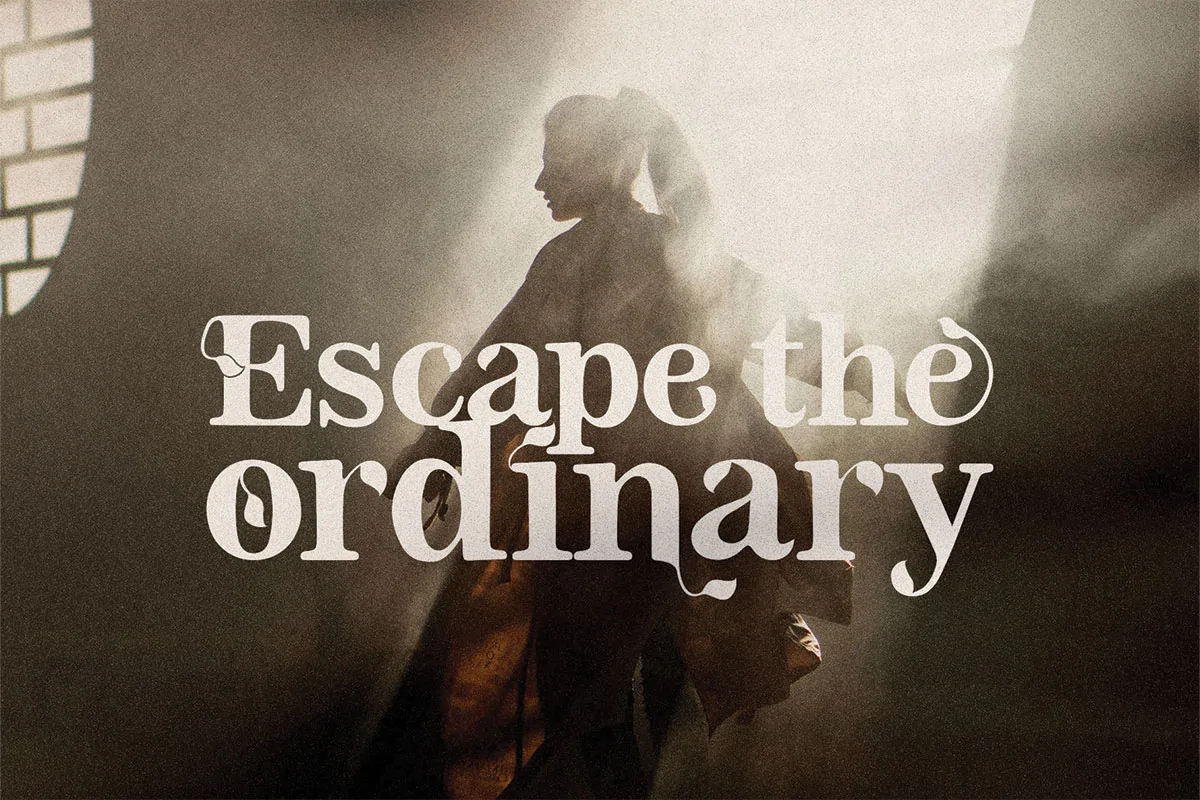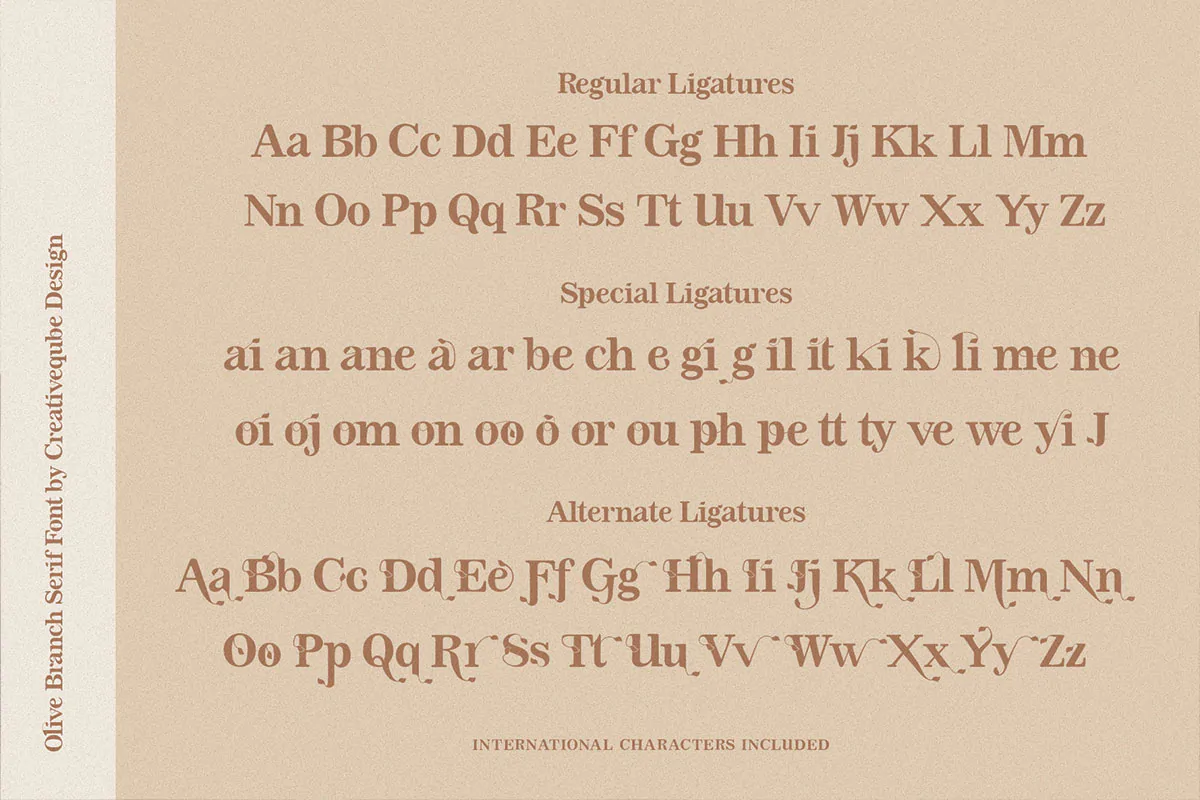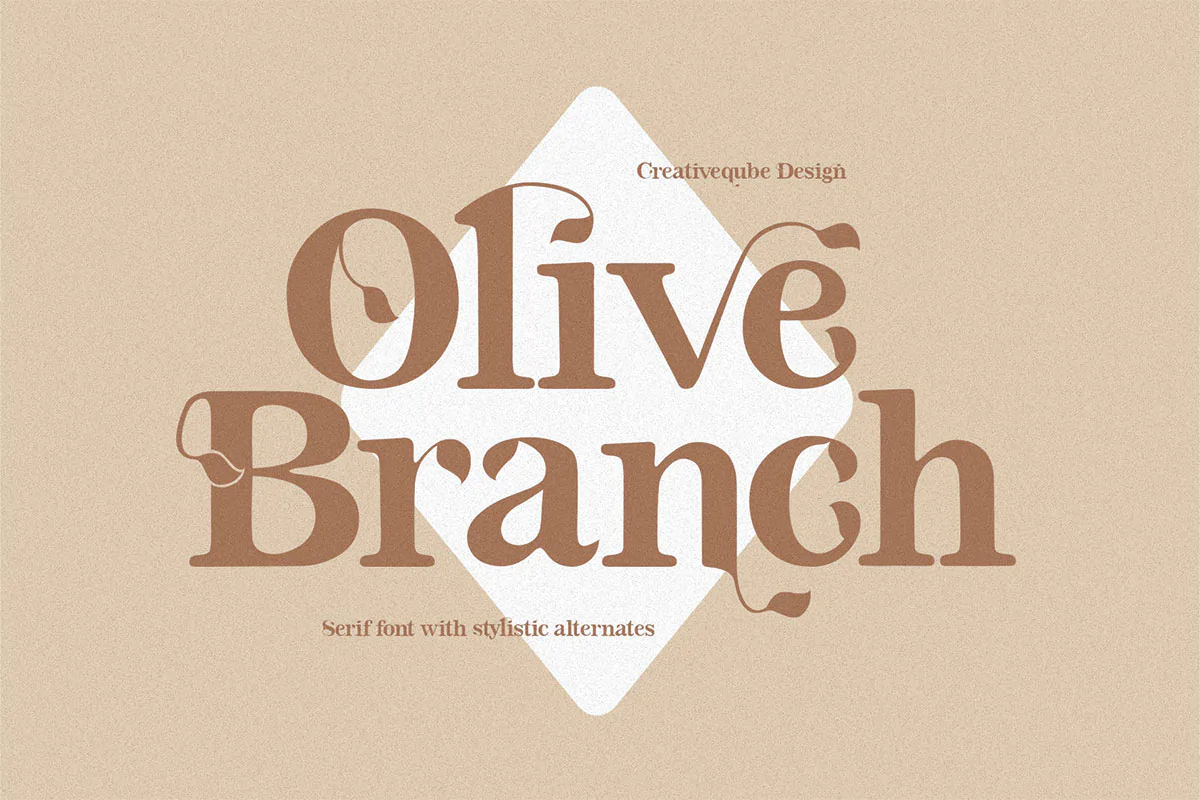
فونت تزئینی شاخه زیتون Olive Branch
فونت تزئینی شاخه زیتون
فونت تزئینی شاخه زیتون Olive Branch یک سریف فونت انگلیسی فوق العاده زیبا است که به سبک فونتهای کلاسیک و سه وزن و استایل مختلف طراحی شده است که از آن میتوانید در طراحی انواع پوستر، کارت تبریک،بسته بندی محصولات، ظروف یکبار مصرف، آرایشی و بهداشتی، لوازم التحریر، پست و استوری رسانههای اجتماعی، اینشات و … استفاده کنید.